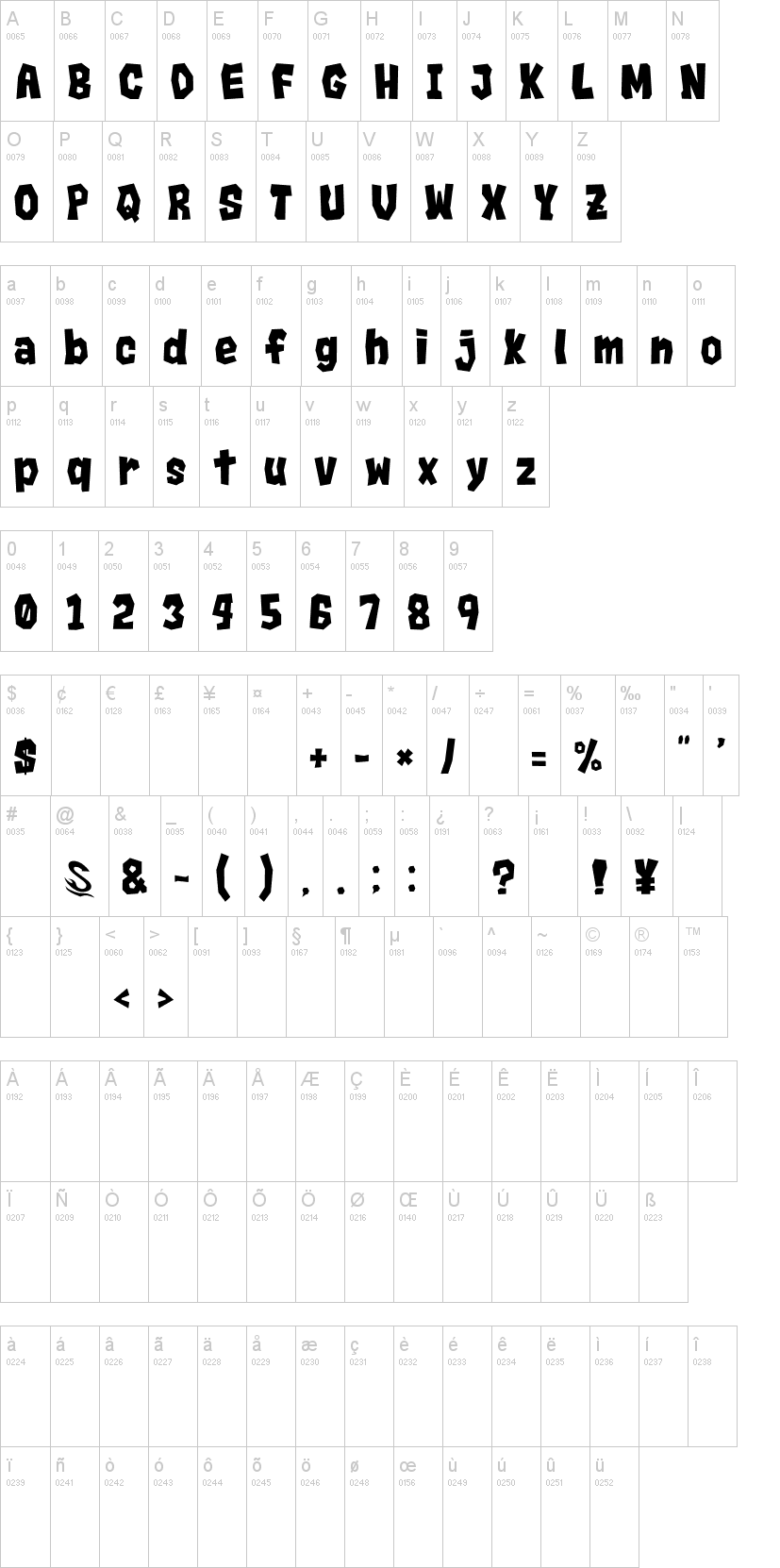
Rocks字体是一款卡通风格的字体,由著名的设计师Riccardo De Franceschi设计,于2016年发布。Rocks字体具有独特的卡通外观,灵活的结构,以及简洁的设计,可以让您的文字看起来更有趣,更有活力。它可以用于各种类型的项目,如广告、海报、标识和网站等,以及各种其他应用场景。内容介绍
Rocks是一款非常不错的手写艺术字体,具有很好的视觉感,适合于文化类的宣传设计、商业类品牌的广告和产品包装设计以及个性化文字排版等较多场景。